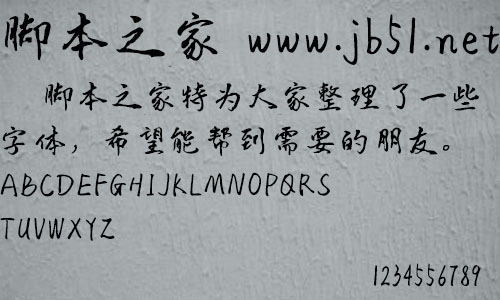
漢儀年紀(jì)輕輕天天念經(jīng)一款不錯的藝術(shù)字體,由漢儀字庫出品,字體筆觸粗實(shí),字形灑脫,具有很好的視覺感,適合應(yīng)用于藝術(shù)設(shè)計(jì)、平面宣傳設(shè)計(jì)、網(wǎng)頁設(shè)計(jì),書法字帖等領(lǐng)域,需要的朋友可以前來本站下載。